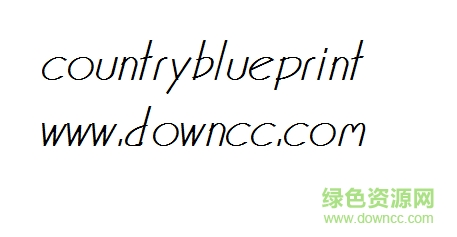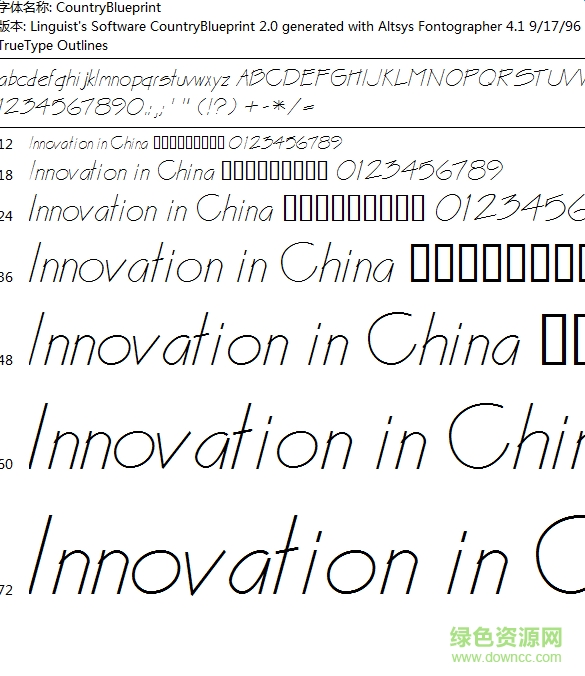
countryblueprint字體是一款手寫(xiě)英文字體,字體筆畫(huà)細(xì)膩,不拖泥帶水,整體效果十分清爽簡(jiǎn)約,非常好看,更多類似字體下載盡在綠色資源網(wǎng)!
countryblueprint字體是一款很不錯(cuò)的電腦英文字體,字體筆畫(huà)隨意,得體大方,看上的朋友歡迎到綠色資源網(wǎng)下載體驗(yàn)!